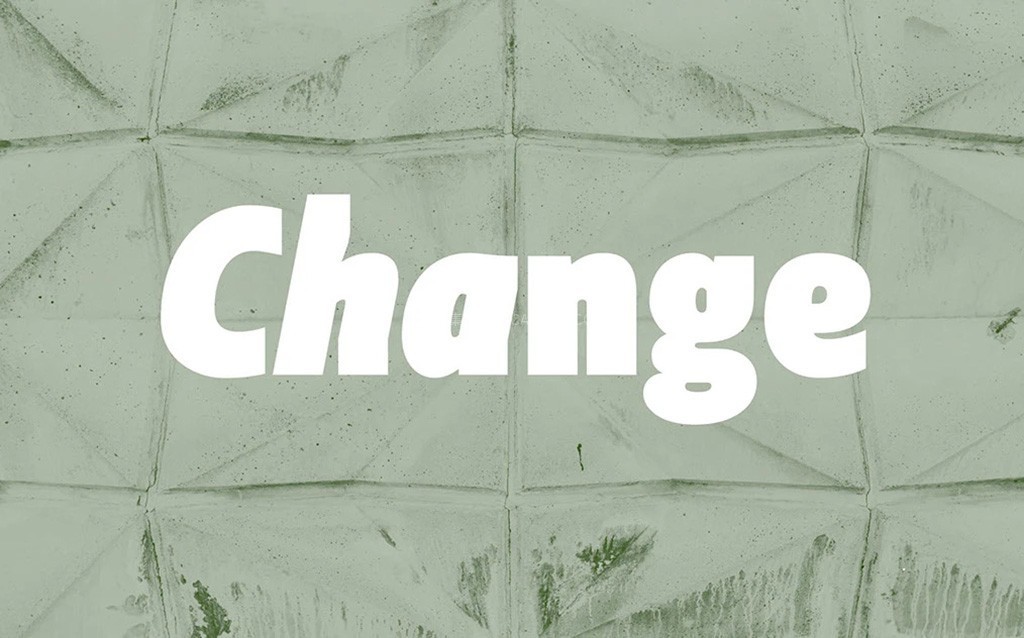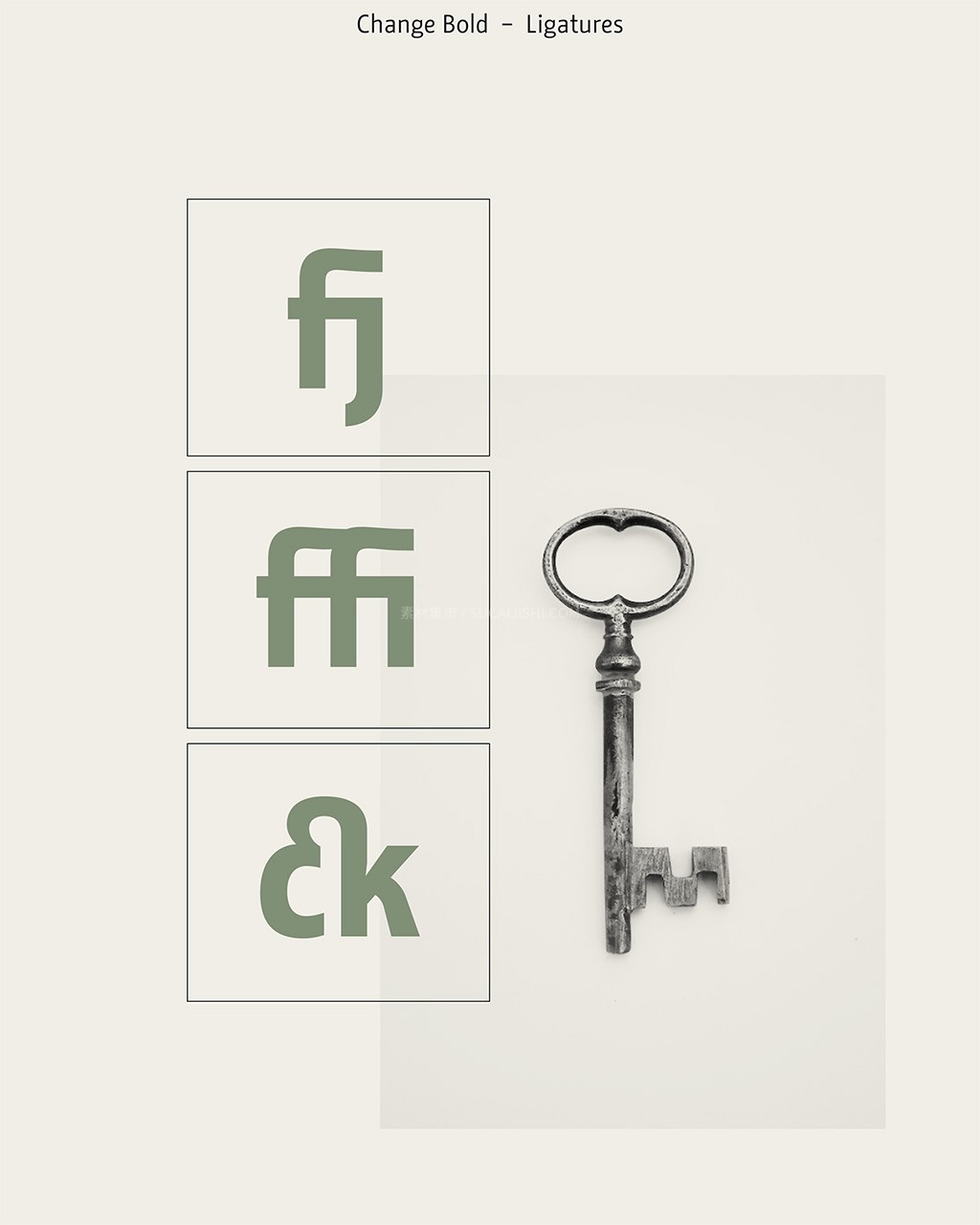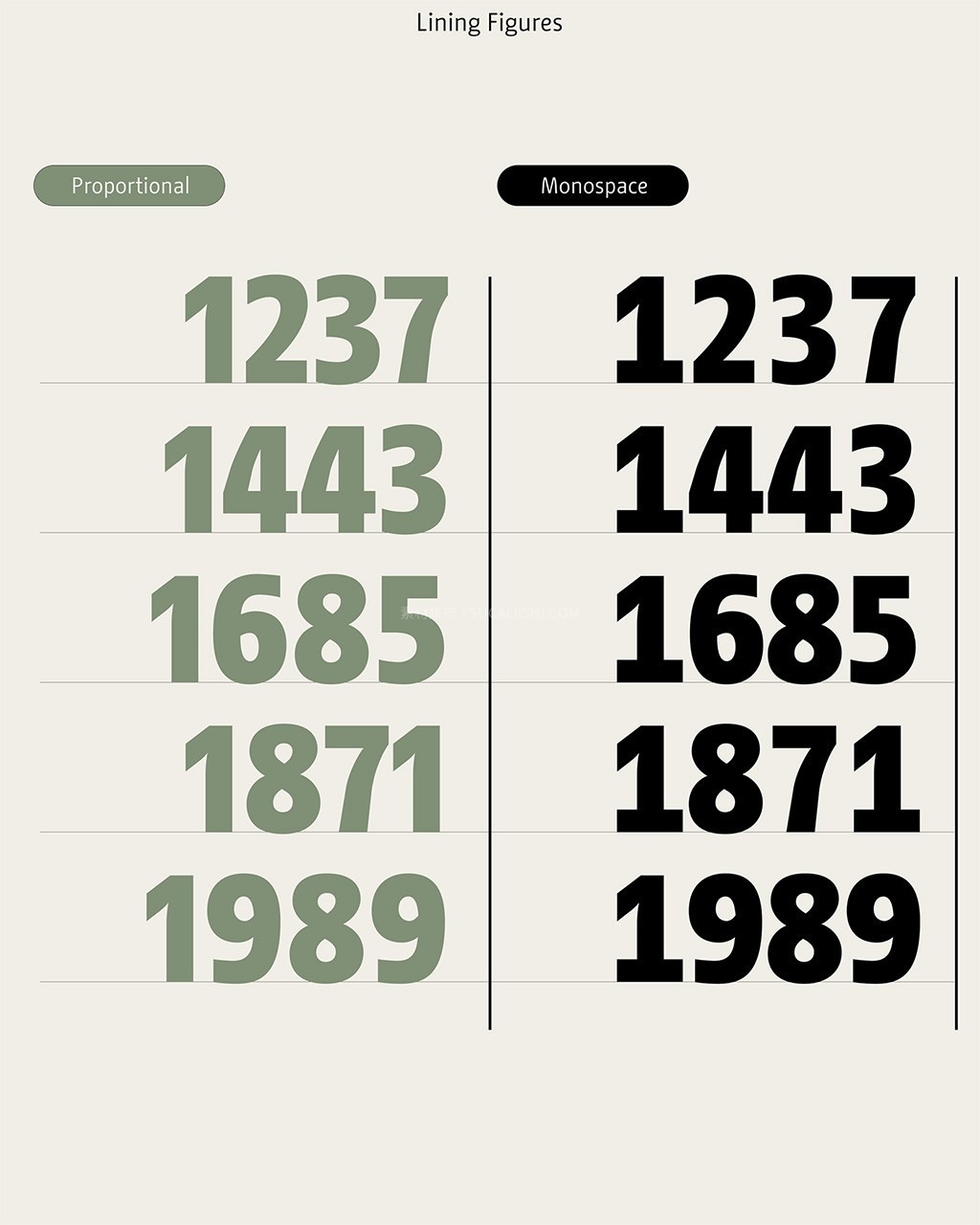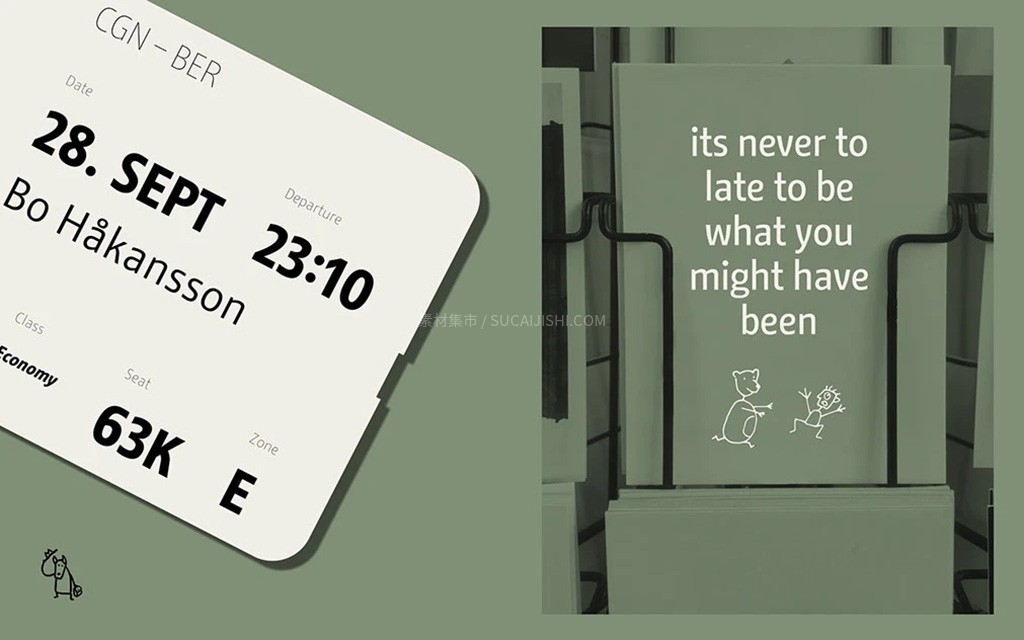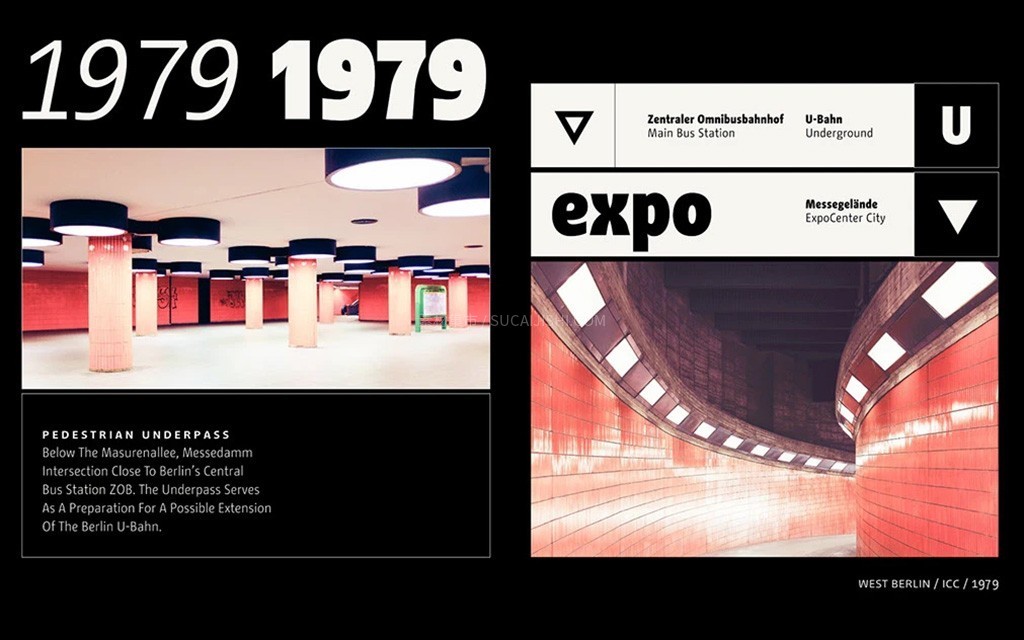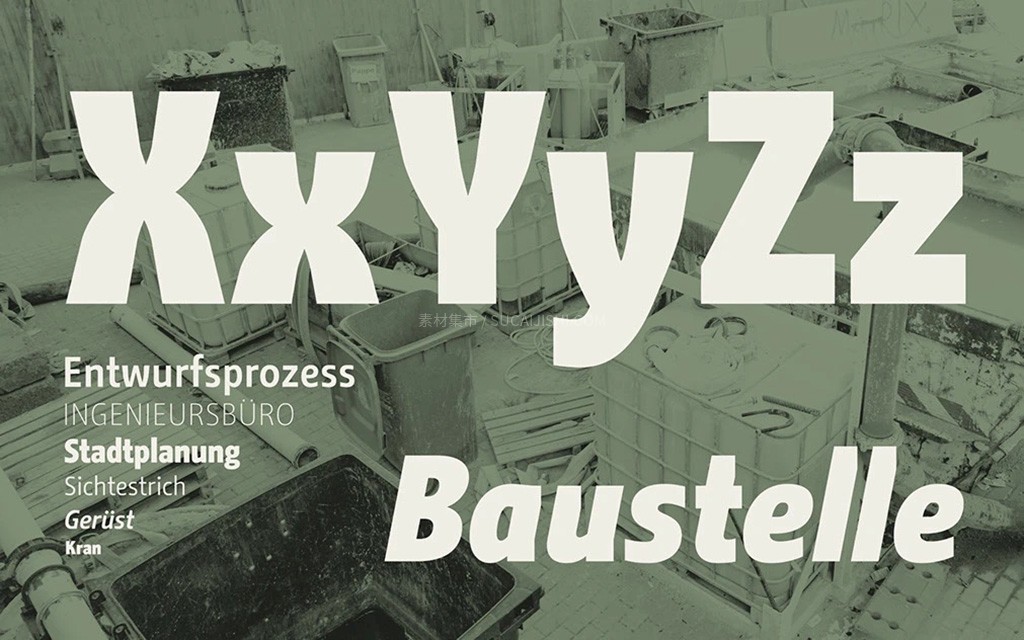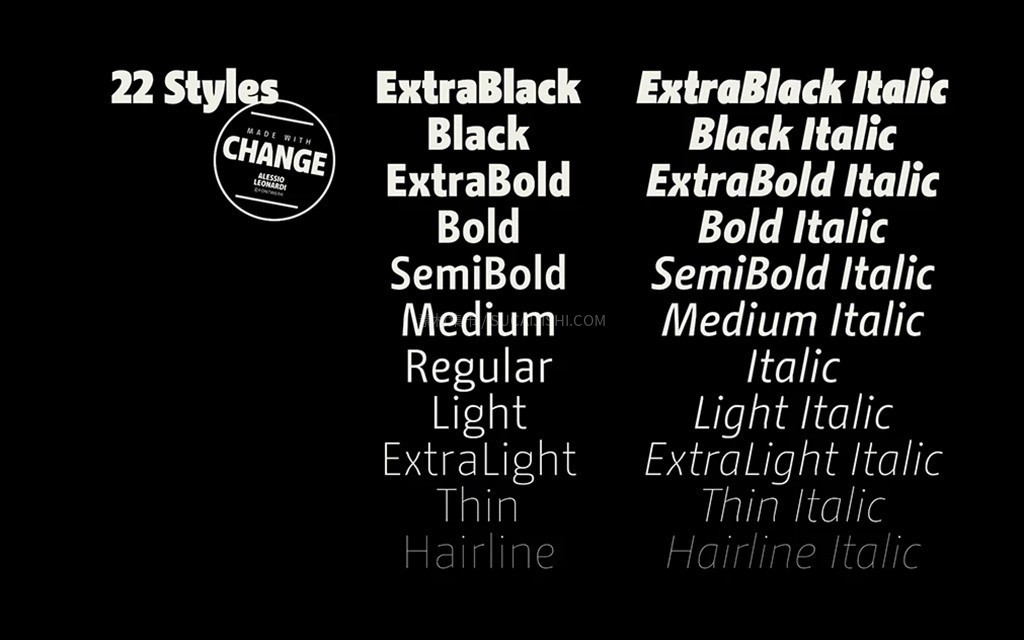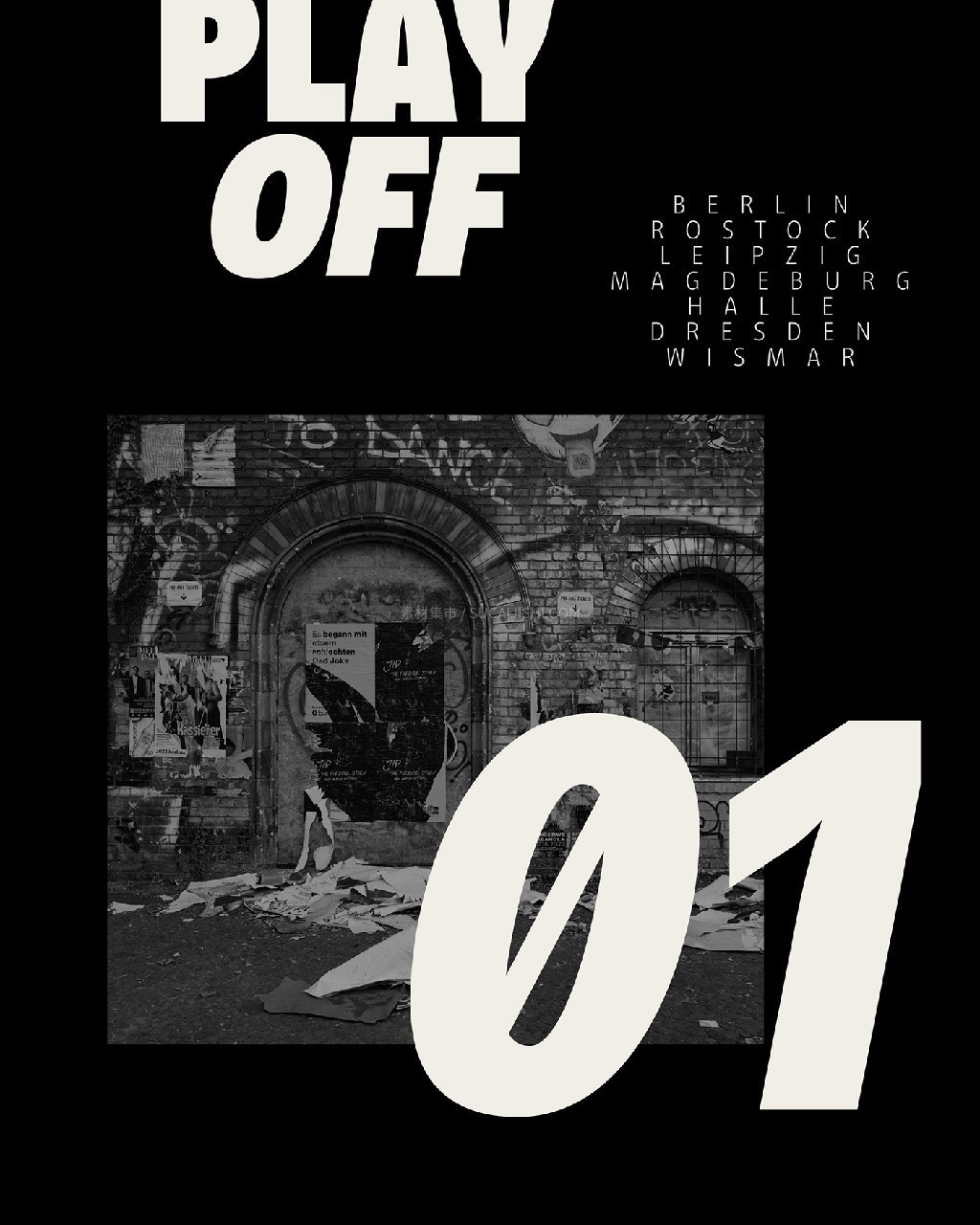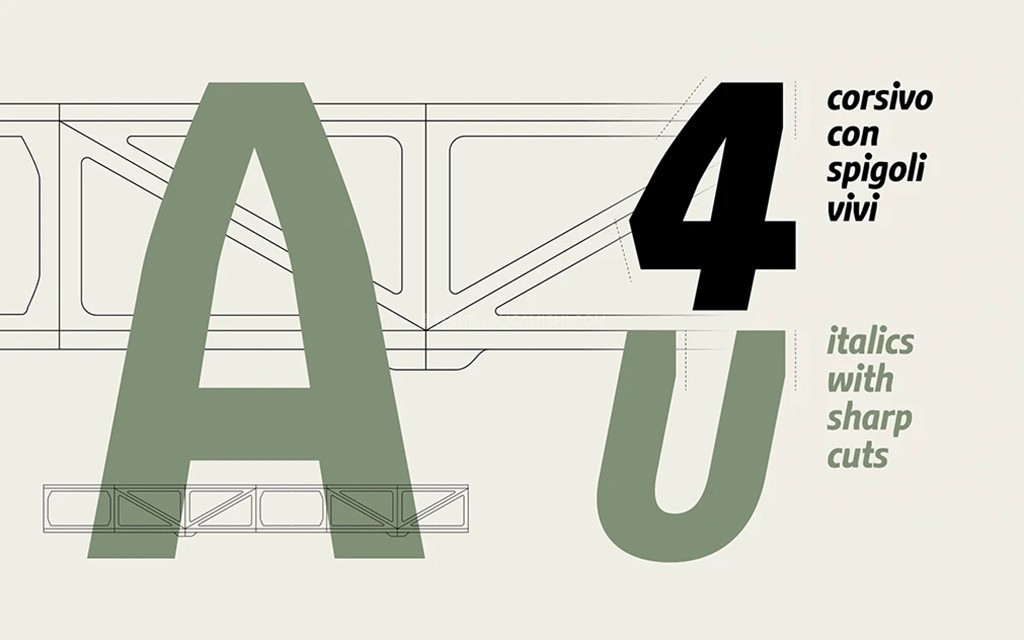
Change 复古风无衬线体字体家族
Change 是一款包含 22 款丰富字重的多用途专业英文字体家族。从极细到极粗,这款庞大的系列为您提供了极大的设计灵活性与跨度。无论是作为大段正文排版,还是用于引人注目的醒目大标题,它都能展现出色的可读性与现代美感。标准 OTF 格式,让您在不同项目中无缝切换,轻松满足全方位的专业设计需求。